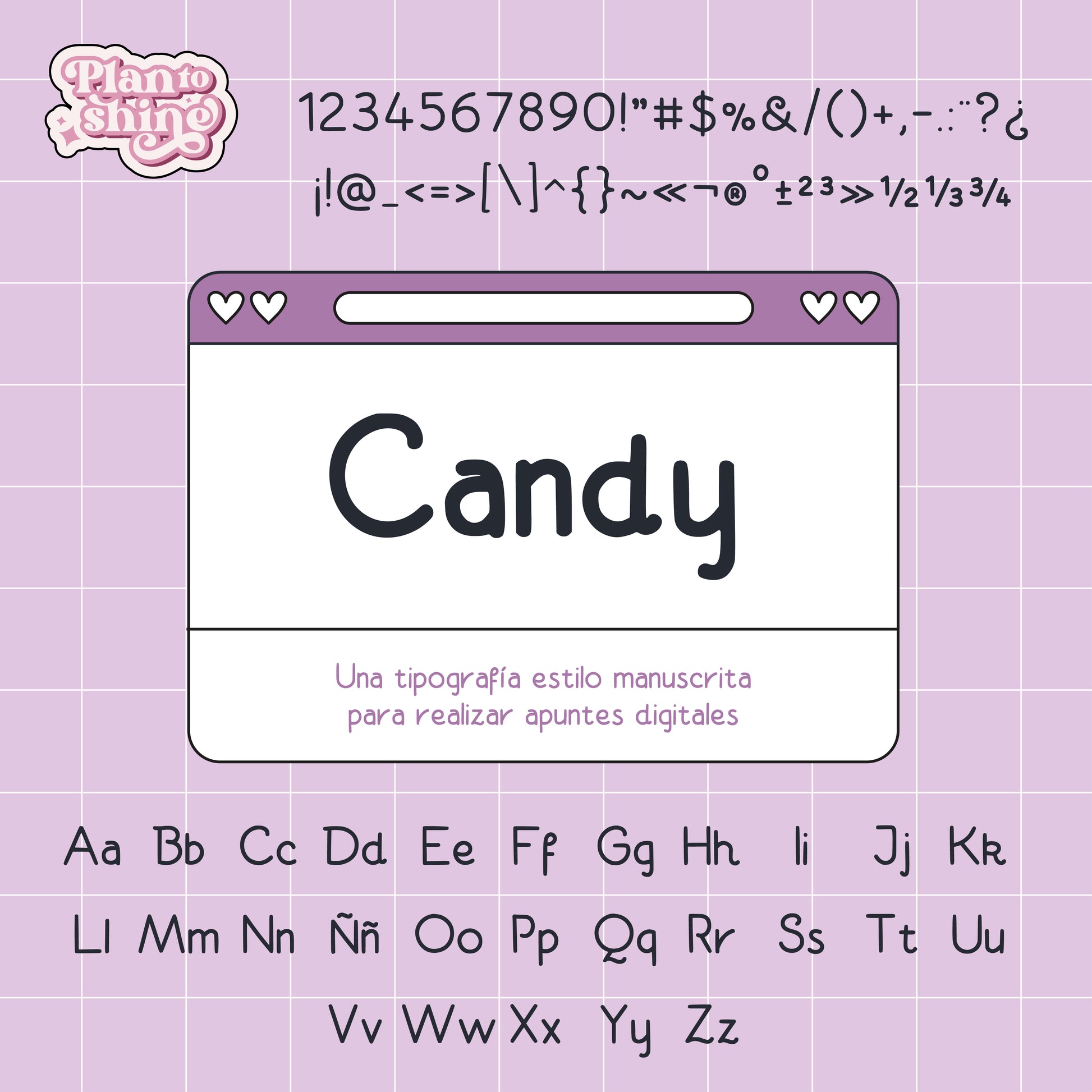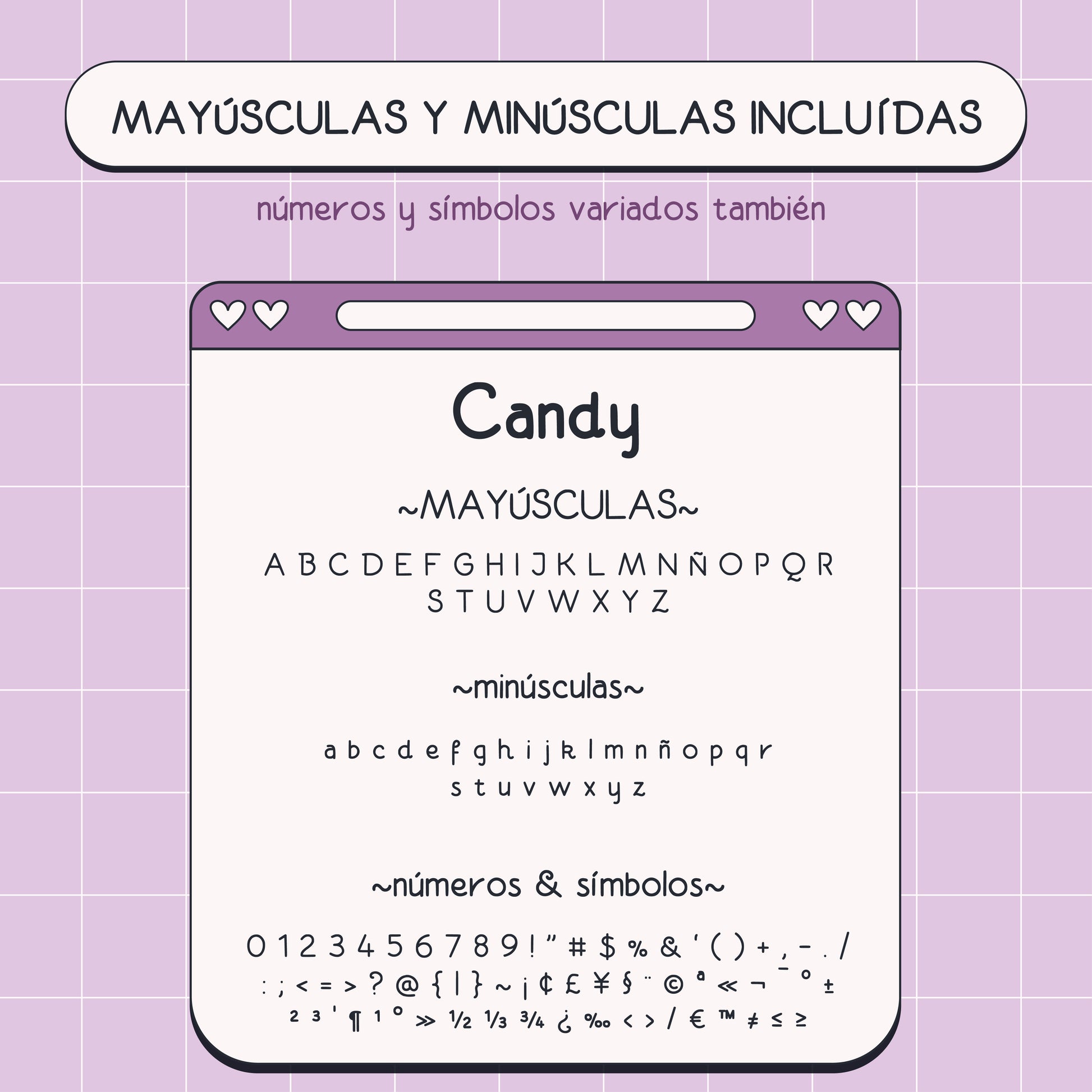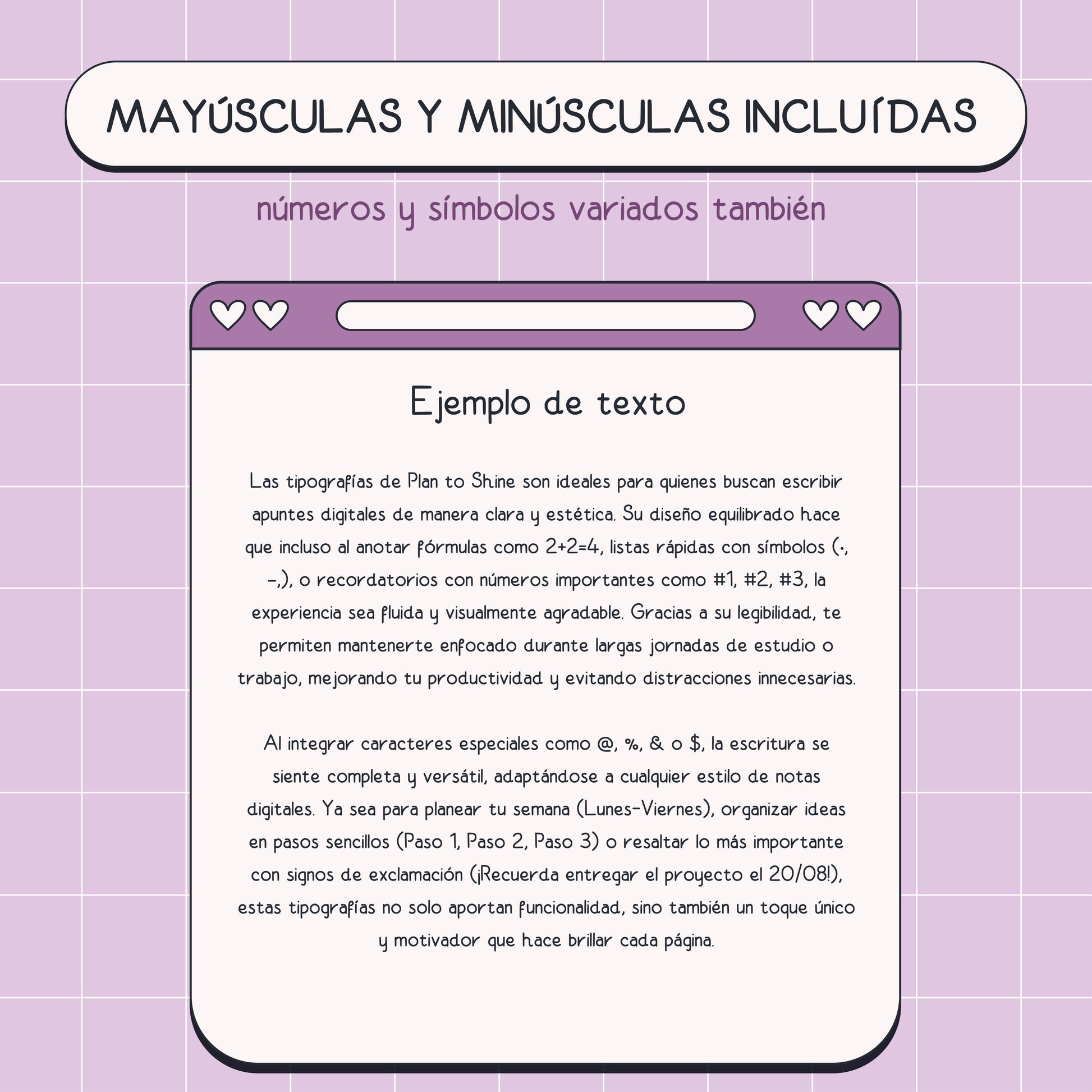
Tipografía Candy
Candy es una tipografía manuscrita divertida y ligera diseñada para apuntes digitales, planners y organización de estudio. Su estilo handwriting transmite un aspecto natural y amigable, perfecto para dar personalidad a tus notas sin perder legibilidad.
La fuente incluye letras mayúsculas y minúsculas, números y símbolos, lo que la hace ideal para escribir títulos, subtítulos y contenido en cuadernos digitales o aplicaciones de notas.
Candy es una excelente opción para estudiantes, creadores y amantes de la papelería digital que buscan una fuente manuscrita bonita para organizar sus apuntes digitales.